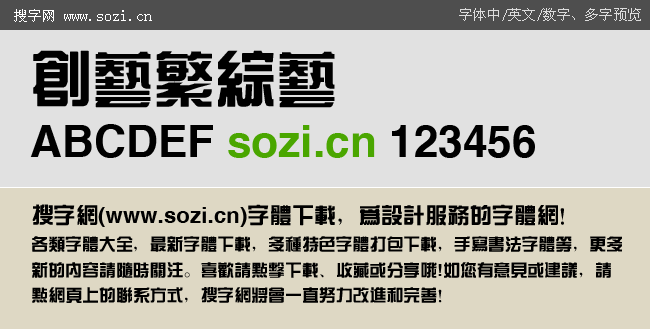
創(chuàng)藝繁綜藝
搜字網(wǎng)提供一款創(chuàng)藝繁綜藝下載。此款字體為繁體字體,綜藝體是黑體的一種變體,也是藝術(shù)字的一種。特點(diǎn)是筆劃更粗,盡量將空間充滿。同時(shí)為了美觀,對(duì)拐彎處的處理較為圓潤(rùn)。適用于廣告、報(bào)刊等的標(biāo)題及海報(bào)展板等設(shè)計(jì)場(chǎng)合使用。